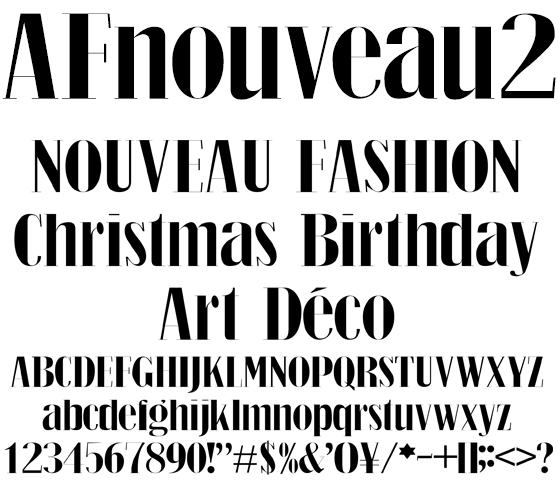
アールデコ調な欧文 AFnouveau2
AFnouveau2
アールデコ調なファッション系ドキュメント、バースデー、クリスマスなどのイベントドキュメントに最適なお洒落な欧文フォント。動画テロップ、Web Server へのアップロード、フォント共有サーバー利用、PDF エンベッド、印刷やロゴなど作成と登録、印影や彫刻、画像化後ソフトへのバンドルなど商用利用できます。